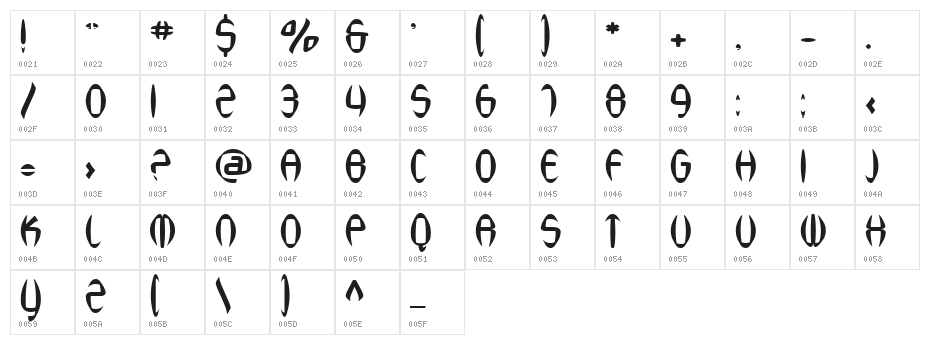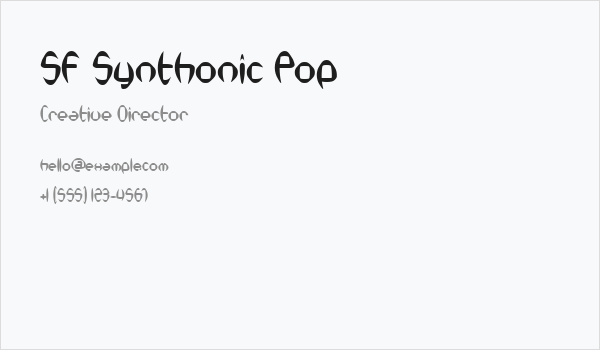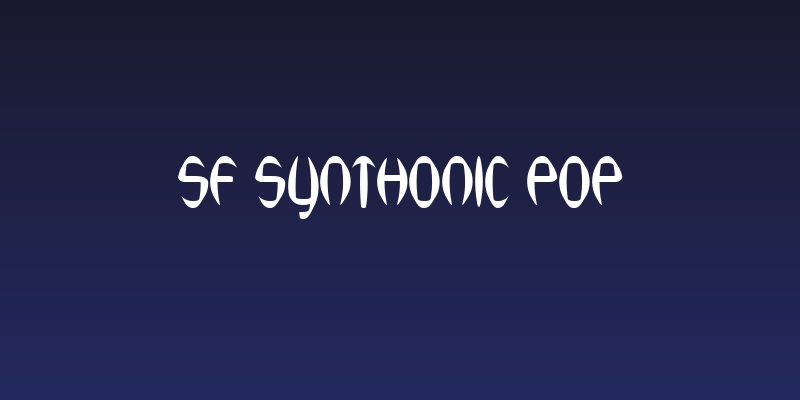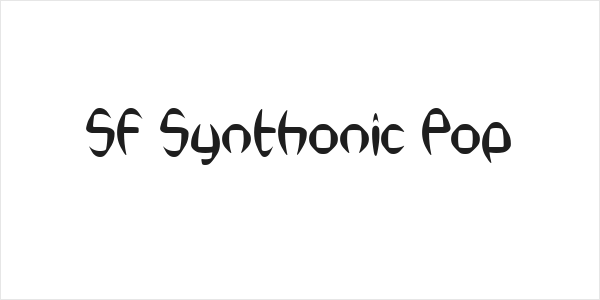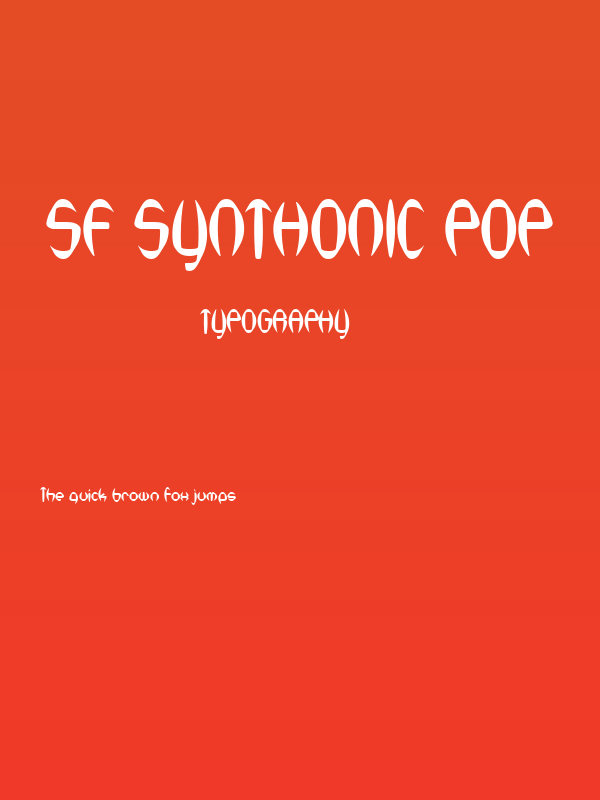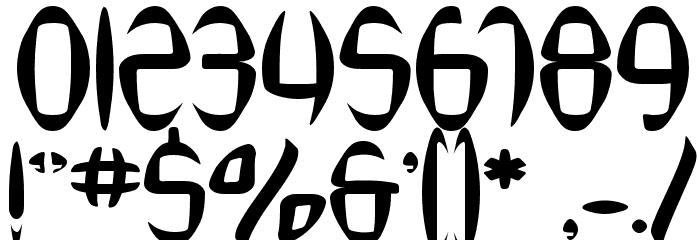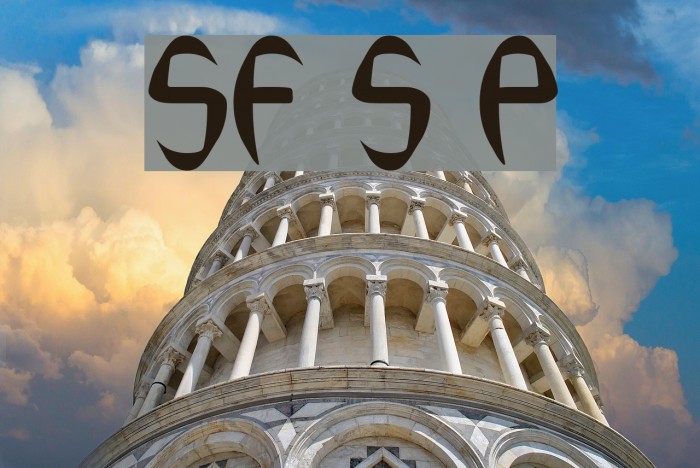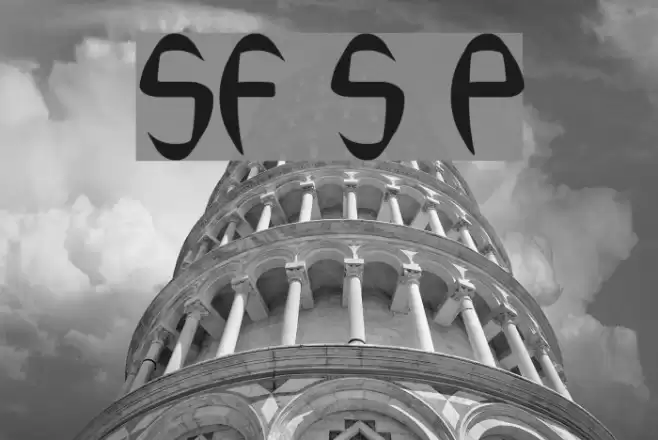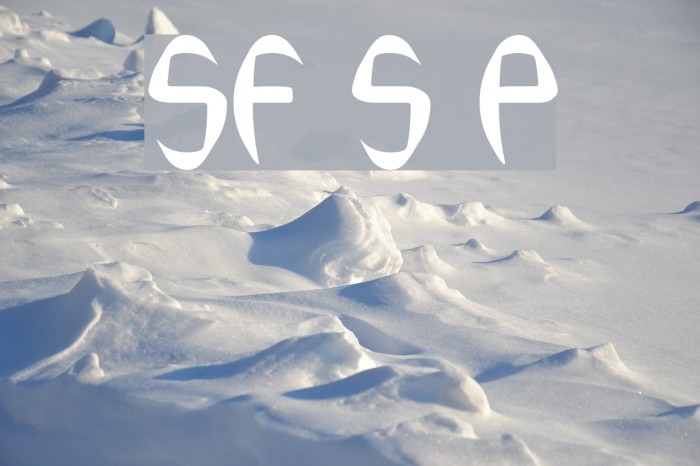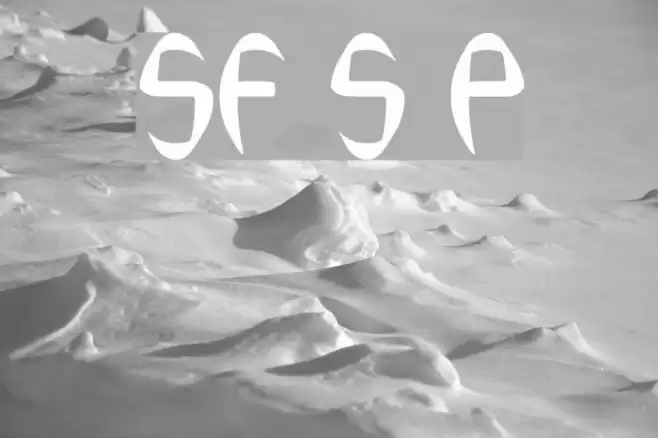
SF Synthonic Pop Font
| 全体的なスタイル | Futuristic |
| おすすめプロジェクト | Ideal for science fiction book covers, movie posters, video game titles, and futuristic branding. |